Rohrfeder
Die »Rohrfeder« ist ein pflanzliches Schreibwerkzeug, das u.a. aus dem Stängeln des Papyrus (Cyperus papyrus), dem Schilfrohr (Phragmites australis), aus Bambus (Bambusoideae) oder Kalmus (Acorus calamus) hergestellt wird. Auch als »Kalamos« von altgr. »kálamos« (κάλαμος), »Calamus« von lat. »calamus« oder »Qalam« von arab. »qalam« (قلم) bezeichnet.
Die Rohrfeder ist ein Schreibgerät, das bereits seit der griechischen Antike in der Kalligrafie benutzt wird und beeinflusst bis heute den Duktus vieler Druckschriften und digitaler Schriften mit Wechselschwung.
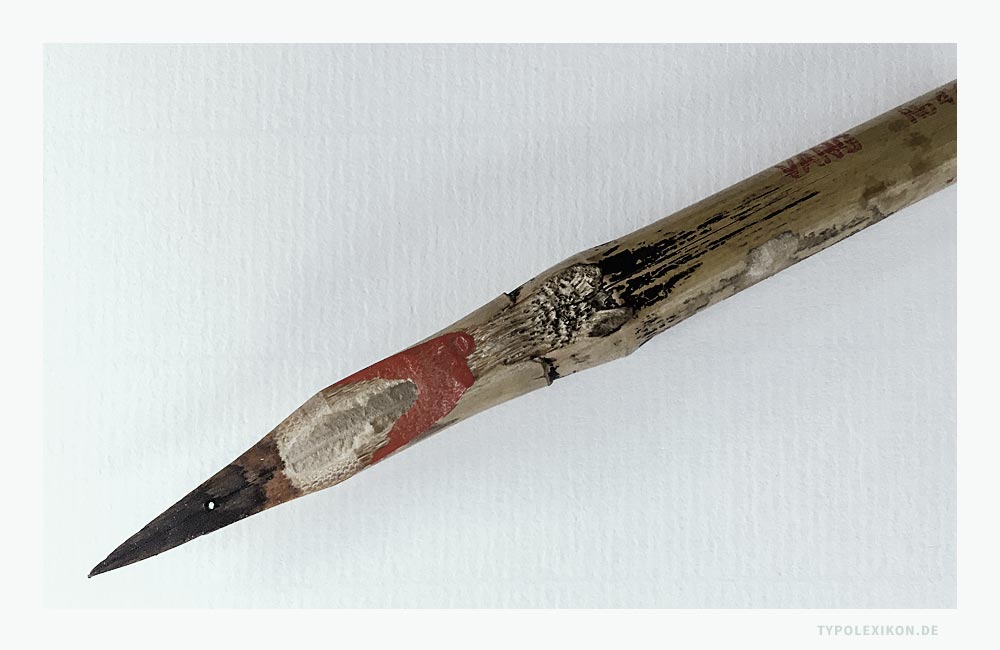
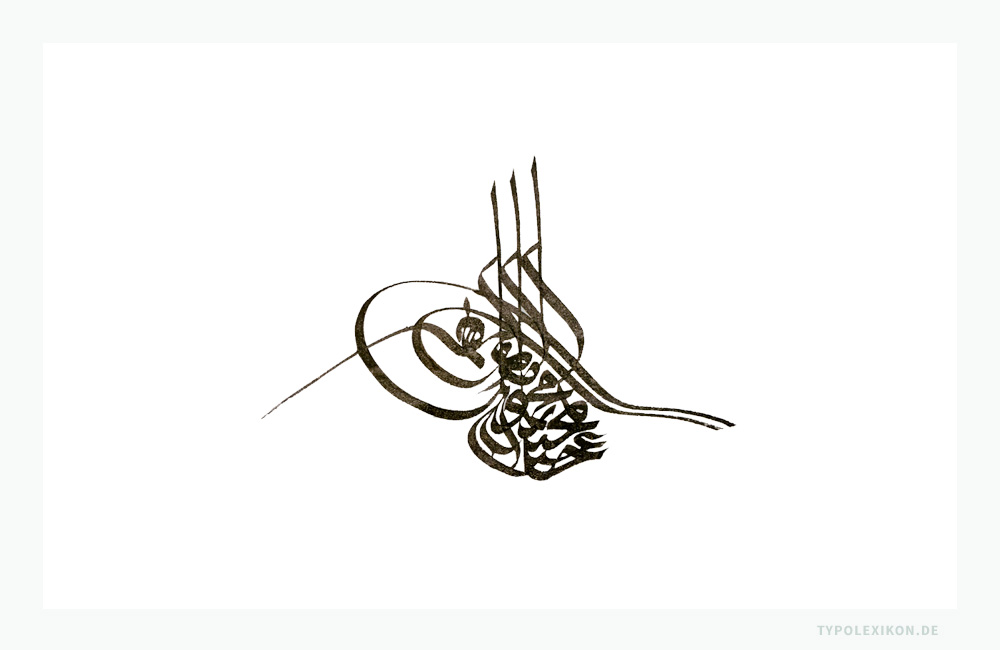
Eine Rohrfeder wird schräg mit einem scharfen Messer an- und nachgeschnitten, der Innenteil ausgeschabt, die Spitze mit einem feinen Einschnitt gespalten und ggf. gepunktet sowie rechtwinklig zur Rohrfeder abgeschnitten, wobei es unterschiedliche Schnittformen gibt, die von spitzem über schmalen bis hin zu breiten Schnitten reichen. 1) Geschrieben wird mit Tinten auf Beschreibstoffen, z.B. aus Papyrus, Pergament oder Papier.
Zu den ältesten lateinischen Verkehrsschriften, die mit der Rohrfeder geschrieben wurden, zählen beispielsweise die Capitalis Quadrata, die Capitalis Rustica und die Scriptura Cursiva.
Dekorative OpenType-Fonts, die auf der Ästhetik der mit der Rohrfeder geschriebenen Schriften basieren, zählen in der Schriftklassifikation zu den Schreibschriften (Script Fonts), die wiederum zu den Zierschriften gehören.